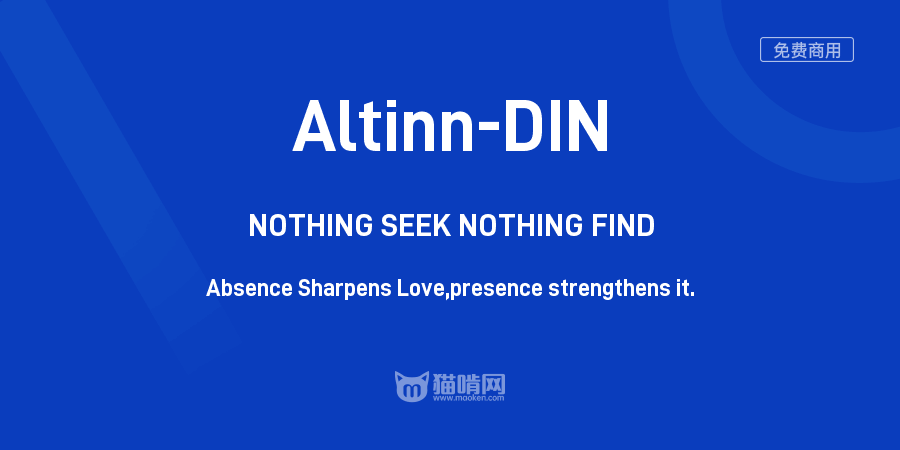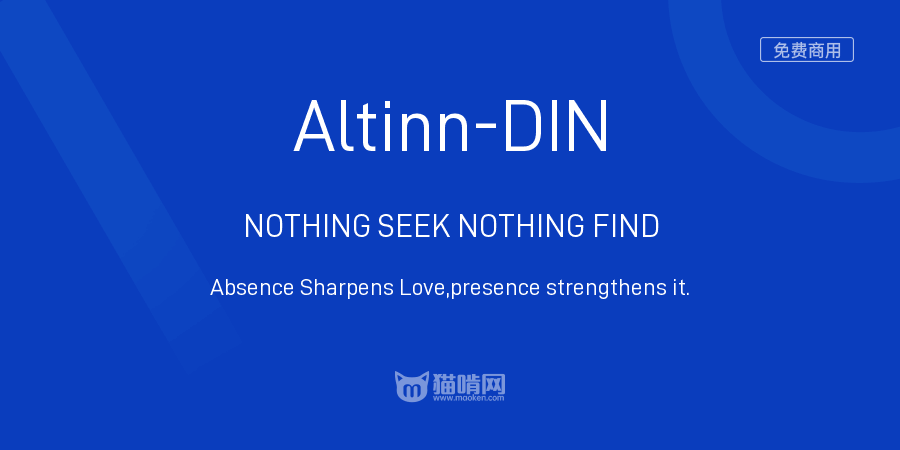
Altinn-DIN
DIN 1451是一种无衬线字体,广泛用于交通、行政和技术应用。
1931年,德国标准机构DIN-Deutsches Institut fur Normang(德国标准化研究所)在标准表DIN 1451 Schriften(字体)中对其进行了定义。类似的标准适用于模版字母。
DIN最初是为工业用途而设计的,第一批DIN字体是一种简化设计,可以在技术难度有限的情况下应用。由于该设计的易读性和简单朴素的设计,它广泛应用于标志,显示改编等用途。原始设计的许多改造字体和扩展已经以数字化形式发布。
Datto使用DIN字体作为主要公司字体,并委托Monotype创建多种样式,供内部使用,并根据SIL Open Font License 1.1许可证进行开源。